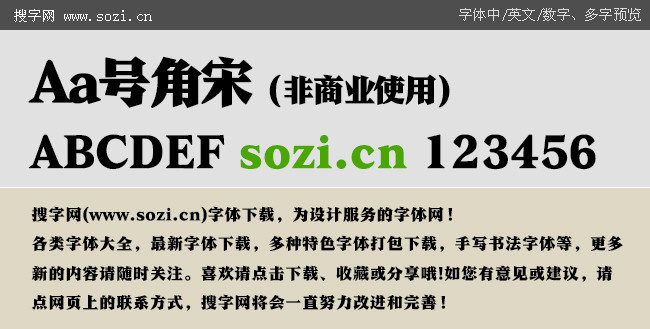
Aa號角宋
搜字網(wǎng)給大家提供一款A(yù)a號角宋(非商業(yè)使用)中文字體下載,該字體是一款醒目的標題字體,表現(xiàn)出鋒銳又具有厚重的形態(tài)。具有強烈的視覺沖擊力,清新簡明。適合書裝設(shè)計、包裝設(shè)計、海報設(shè)計等應(yīng)用(此字體為個人非商用版,商用可以聯(lián)系QQ:1006760504)。